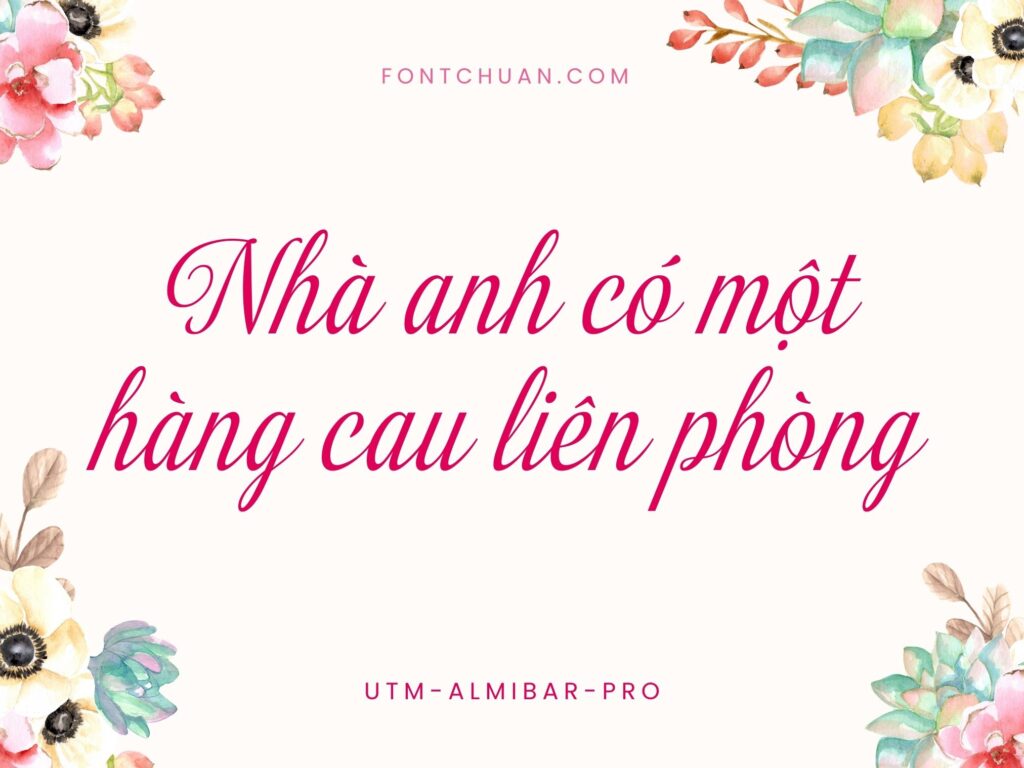
Font UTM Almibar Pro Việt Hóa
Almibar Pro là một Font Script thanh lịch được thiết kế bởi Manuel Eduardo Corradine và phát hành bởi Corradine Fonts vào năm 2012. Với phong cách mềm mại và uyển chuyển đặc trưng của chữ viết tay cổ điển, font này nhanh chóng trở thành lựa chọn phổ biến trong giới thiết kế yêu thích sự tinh tế. Phiên bản Việt hóa được thực hiện bởi Đinh Kiên, hỗ trợ đầy đủ tiếng Việt cùng hơn 100 ngôn ngữ khác. Font đã được thành viên Font Chuẩn sưu tầm và chọn lọc để ứng dụng linh hoạt trong các thiết kế cần sự sang trọng và giàu cảm xúc.
Almibar Pro sở hữu hệ thống ký tự liền mạch, độ mảnh nhất quán và các đường lượn mượt mà. Font có nhiều ligature đẹp mắt, phù hợp với các thiết kế thiệp mời, tiêu đề trang trí, menu nhà hàng, bao bì cao cấp hoặc nhận diện thương hiệu cho các sản phẩm tinh tế. Những ngành nghề như quảng cáo, thiệp cưới, giáo dục và ẩm thực có thể tận dụng tốt Almibar Pro để tạo sự mềm mại và lôi cuốn trong bố cục thiết kế.